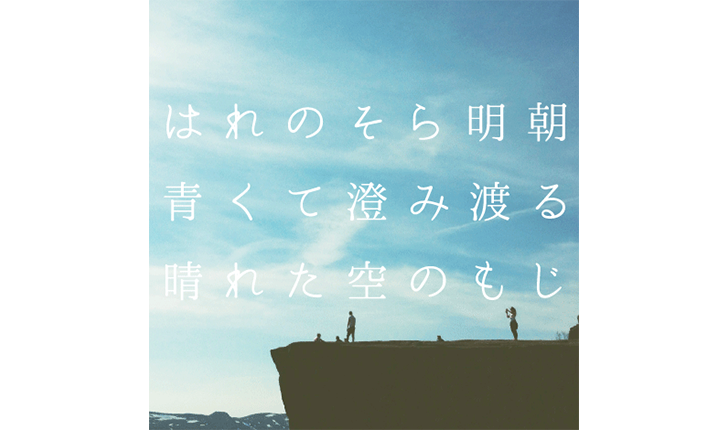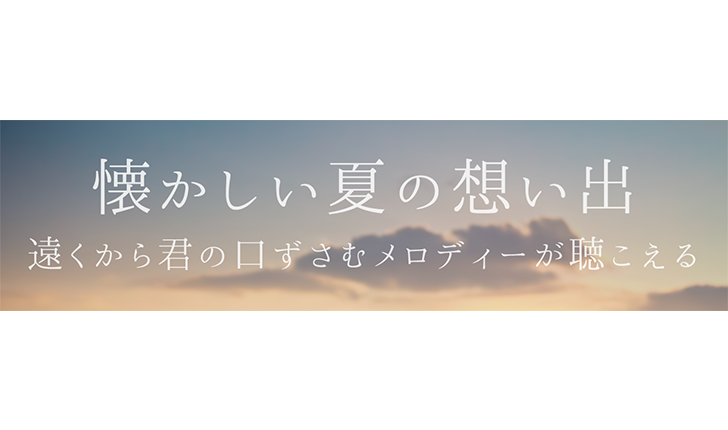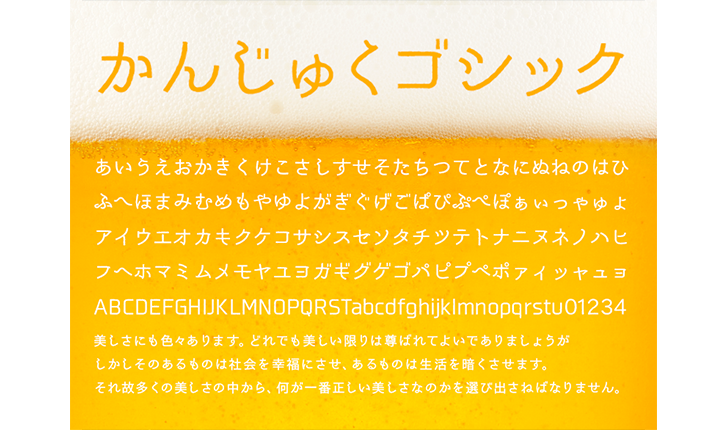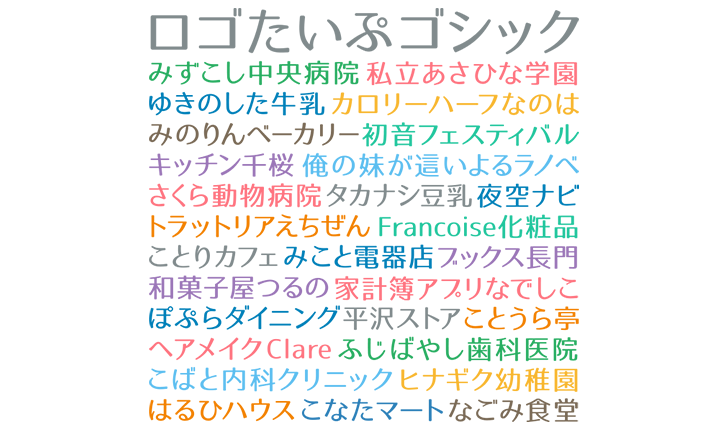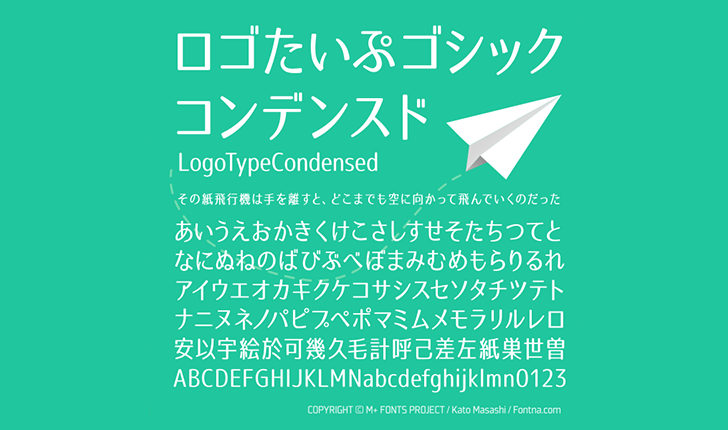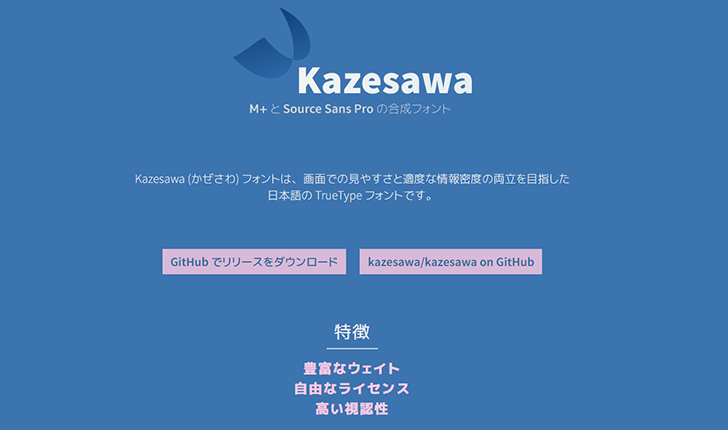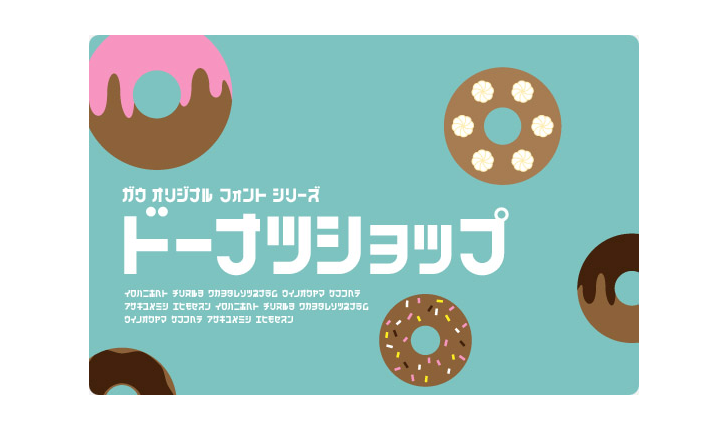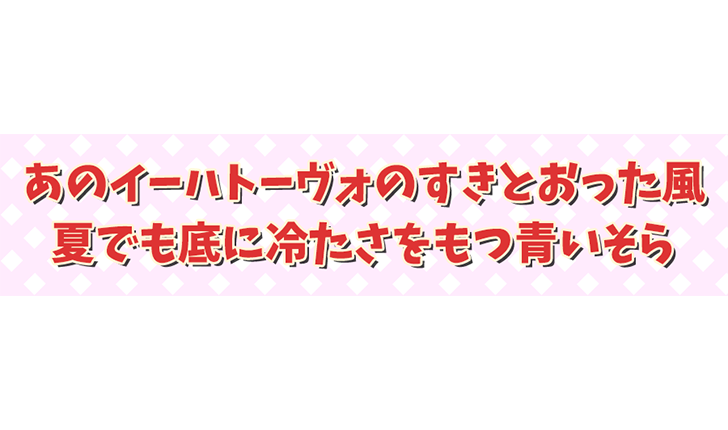
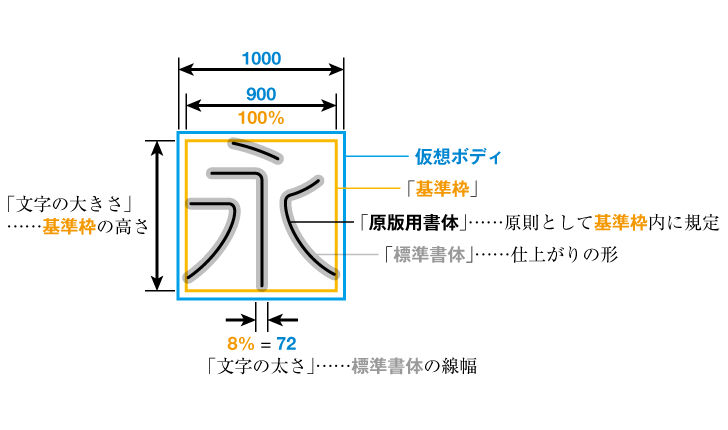
個人、商用で利用することができる、かっこいい日本語のフリーフォントを紹介します。
クールなひらがな、スタイリッシュなカタカナ、インパクトのある漢字など、かっこいいデザインによく合うフォントを揃えました。
かっこいい日本語のフリーフォント一覧
超極細ゴシック体
超極細ゴシック体は、Extra Lightのフォントよりもさらに細い、超極細のフォントです。無機質で真っ直ぐな線が特徴的な、クールな仕上がりになっています。無料でダウンロードできて、商用利用可能です。
源暎ラテン(源暎ラテゴ/ラテミン)
源暎ラテンは、漫画のスピーカーセリフなどに使えるラテン体のフォントです。源暎ラテゴと源暎ラテミン、2種類のフォントがあります。どちらもひらがな、カタカナは共通ですが、源暎ラテゴは源暎ゴシックの漢字が、源暎ラテミンは源暎ゴシック Lightの漢字を横太に処理した漢字が使われています。無料でダウンロードできるフリーフォントです。
はれのそら明朝
はれのそら明朝は、角丸の、すっきりとした明朝体フォントです。オールド明朝体の特徴も持っている日本語フォントです。無料でダウンロードできて、商用で使えます。
ほのか明朝
ほのか明朝は、明朝系の日本語フォントです。少しクセのある曲線が特徴的で、通常の日本語フォントよりもかな文字が小さめにデザインされています。どこか懐かしさのある、夏の夕空のような、澄み切った、爽やかな仕上がりになっています。商用利用可能なフリーフォントです。
かんじゅくゴシック
かんじゅくゴシックは、熟成された味わいのあるレトロなフォントです。文字に切れ込みがある、個性的な仕上がりになっています。漢字が第二水準まで含まれた、商用可のフリーフォントです。
刻明朝フォント
刻明朝フォントは、明朝体の漢字に、人工的で硬さのある小さめのひらがな、カタカナを組み合わせたフォントです。かなもじはアルファベットのセリフ体のようなうろこを持っています。商用利用可能なフリーフォントです。
刻ゴシックフォント
刻ゴシックフォントは、スタンダードなゴシック体の漢字に、縦長で小さめのひらがな、カタカナを組み合わせたフォントです。直線的な形の、モダンでかっこいいフォントに仕上がっています。商用利用可能なフリーフォントです。
ロゴたいぷゴシック
ロゴたいぷゴシックは、ロゴタイトルや見出し向けのフォントです。かっこいい感じと、エレガントで優しい感じを併せ持った、楽しい雰囲気のフォントです。商用、非商用問わず利用することができます。
ロゴたいぷゴシック-コンデンスド
ロゴたいぷゴシック-コンデンスドは、ロゴや見出しに使えるフォントです。漢字も収録されており、すっきりとした、風通しのいいデザインが特徴的です。非商用、商用どちらでも利用することができます。
FGニューれとろ
FGニューれとろは、ひらがなのうねりが特徴的なフォントです。レトロな懐かしさとモダンなデザインが融合したような仕上がりです。書籍「続・和文フリーフォント集」に収録されています。
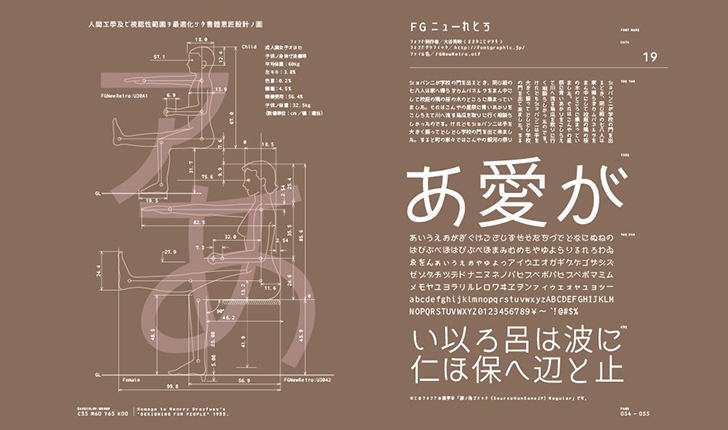
源真ゴシック
源真ゴシックは、AdobeとGoogleが3年をかけて開発した美しいフォント「源ノ角ゴシック」をベースに、デザインソフトで扱いやすいTrueType形式に変換、調整をしたフォントです。等幅とプロポーショナルが用意されています。大きい文字も小さい文字も読みやすく、パワーポイントなどで使用すると文字をはっきりと見せることができます。
M+ FONTS
M+ FONTSは、5000文字以上の漢字をカバーした、使い勝手のいい日本語フォントです。直線の処理と柔らかな曲線が対象的な、おしゃれで、かっこいい仕上がりになっています。10年以上制作が続けられており、高品質なフォントにもかかわらず、無料で利用することができます。
Kazesawa フォント
Kazesawa フォントは、画面での見やすさを重視して作成されたフォントです。フォントのウェイトも6種類用意されており、細い文字の繊細な表現から、太い文字の力強い表現まで、幅広い使い方ができます。
JKゴシックL
JKゴシックLは、女子高生風のかわいいフォントです。かわいらしい丸文字のフォントですが、青春のキラキラとした爽やかさを感じるデザインです。
ドーナツショップ
ドーナツショップは、ドーナツショップで見かけるような、ポップでかっこいい感じのフォントです。カタカナのみが収録されています。商用利用可能なフリーフォントです。
万代スポーツフォント
万代スポーツフォントは、力強さのある、少し昭和レトロな印象のフォントです。1956年創業のスポーツ用品店の看板の文字をベースに作成されています。スポーツにぴったりな、かっこいい仕上がりです。カタカナのみの収録です。寄付での購入か、SNSへのシェアでの無料ダンロードかを選ぶことができます。
けいふぉんと
けいふぉんとは、「けいおん!」のロゴタイプをベースに作成されたフォントです。軽音部の青春のような、軽快で、ロックで、ポップなデザインです。特にひらがなとカタカナはとてもリズミカルな仕上がりになっています。けいおん!の作品イメージどおり、素直で、明るい印象のフォントです。無料でダウンロードできて、商用利用可能です。
イバラ字
イバラ字は、バラのトゲのように、尖った字系のフォントです。イバラの刺々しさが表現された、かっこいいフォントになっています。フリーで商用可のフォントです。
自由の翼フォント
自由の翼フォントは、進撃の巨人のオープニングテーマで使われている書体をベースに作成された、二次創作フォントです。元の作品のイメージどおりの、クールでかっこいい仕上がりです。商用利用可能なフリーフォントです。
機械彫刻用標準書体
機械彫刻用標準書体は、工業彫刻に使われる日本工業規格(JIS)で定められた書体で、これをデジタル化したものです。工業彫刻独特の機能的な美しさを持っています。フリーの日本語フォントです。